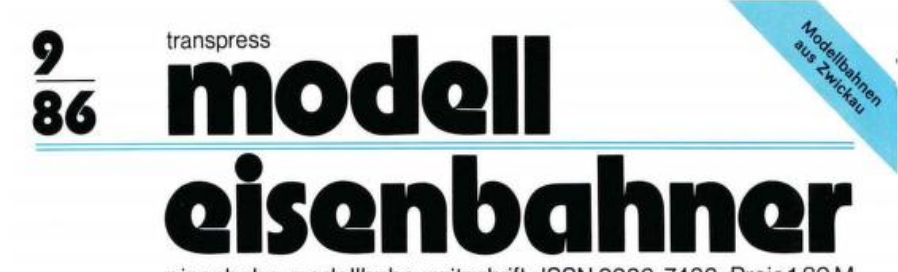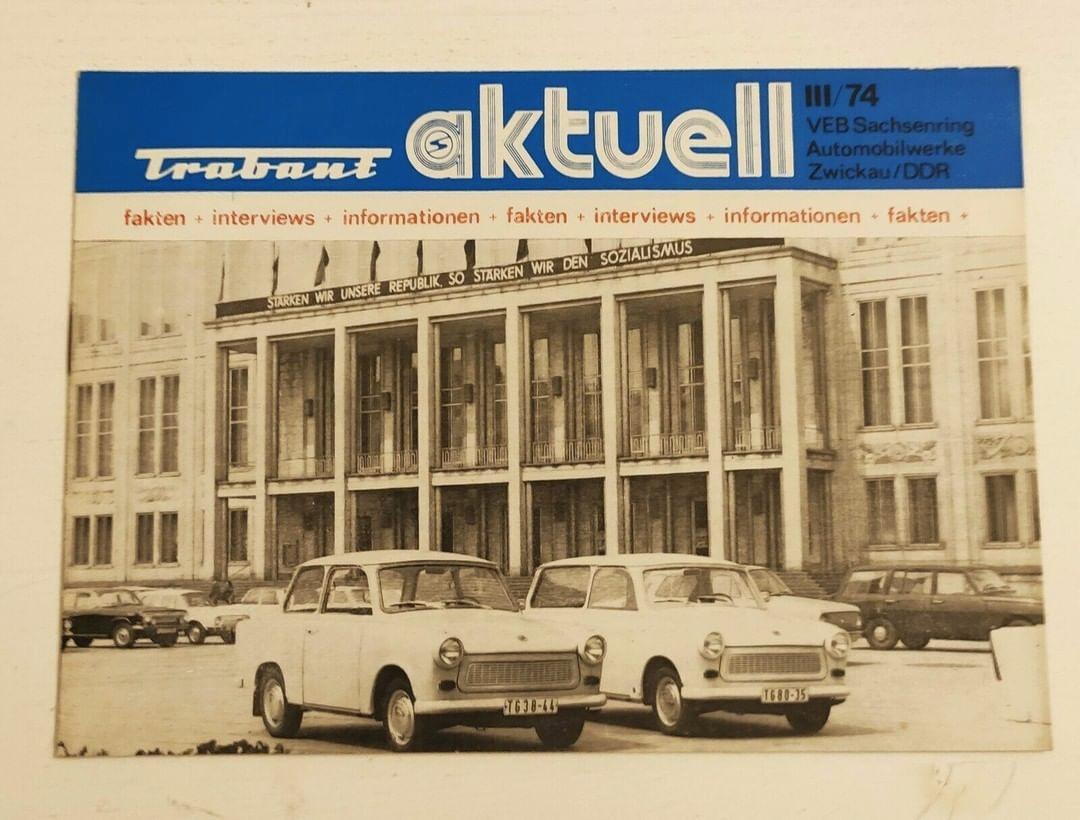
Schriftart DDR-Zeitschrift Modelleisenbahner der 80er
ich suche eine Schriftart, die ähnlich der STOP aussieht, aber Unterschiede aufweißt. Ich habe deinen Ausschnitt aus der Zeitschrift Modelleisenbahner von 1988 und von einem Prospekt von 1974 angehängt. Das Beispiel von 1974, glaube ich, ist eine Abwandlung.